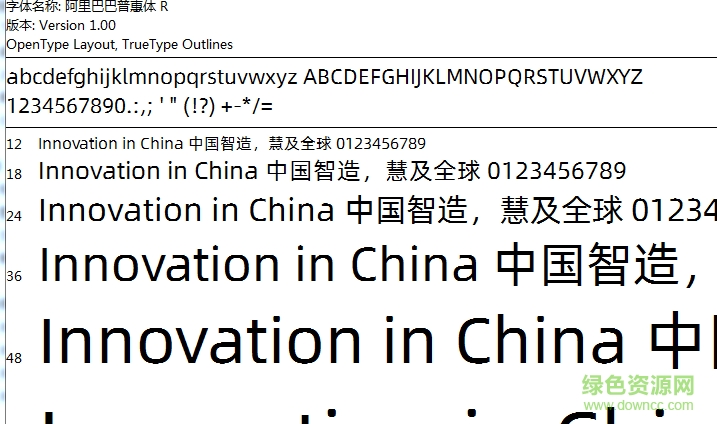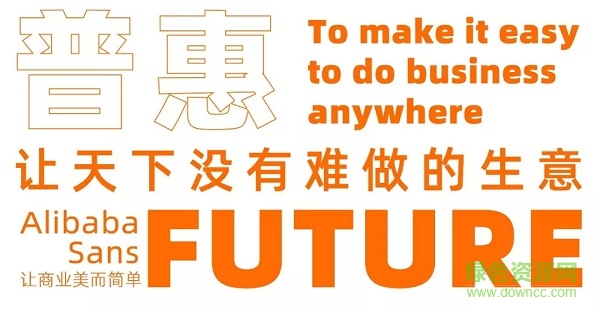
造以此字
獻(xiàn)禮阿里巴巴20周年,細(xì)入微見(jiàn)字之美,用其字品商之道,阿里巴巴普惠體,讓商業(yè)美而簡(jiǎn)單
多場(chǎng)景
中文5個(gè)字重,西文11個(gè)字重,滿(mǎn)足多業(yè)務(wù)應(yīng)用場(chǎng)景的組合表現(xiàn)需求。
全球化
收錄11.6萬(wàn)漢字,7205個(gè)拉丁字母,覆蓋173個(gè)語(yǔ)種,滿(mǎn)足阿里巴巴集團(tuán)及其生態(tài)的全球化業(yè)務(wù)需求。
年輕化
筆畫(huà)簡(jiǎn)潔,造型瘦長(zhǎng),重心較高,充分展現(xiàn)20歲阿里少年額精氣神。
這一次可免費(fèi)商用的阿里巴巴普惠體共有 Light / Regular / Medium / Bold / Heavy 5個(gè)字重,其中 L/R/M/B 4個(gè)字重按照 GB18030 字符集標(biāo)準(zhǔn)制作,各包含 28983 個(gè)字符,而 H 則遵循 GB2312 標(biāo)準(zhǔn),包含 8213 個(gè)字符,西文部分漢儀字庫(kù)西文組擴(kuò)展了日文假名、漢語(yǔ)拼音、臺(tái)灣注音符號(hào)等,最終共計(jì) 124145 個(gè)字符??梢詽M(mǎn)足阿里巴巴集團(tuán)及其經(jīng)濟(jì)體公司在全球化業(yè)務(wù)下的多個(gè)應(yīng)用場(chǎng)景需求。
據(jù)阿里巴巴定制字體項(xiàng)目負(fù)責(zé)人、阿里巴巴集團(tuán)品牌-高級(jí)創(chuàng)意設(shè)計(jì)專(zhuān)家羿光介紹,從去年 6 月至今,整套阿里巴巴普惠體的設(shè)計(jì)歷時(shí) 10 個(gè)月,“不僅要包含突顯企業(yè)品牌個(gè)性的標(biāo)題字,還要囊括更為實(shí)用的內(nèi)文字,兼顧多個(gè)場(chǎng)景下的應(yīng)用……這么大體量的字體設(shè)計(jì)并面向全場(chǎng)景開(kāi)放授權(quán)免費(fèi)商用,開(kāi)創(chuàng)了中國(guó)企業(yè)造字的先河?!?/p>
中文字體多采用現(xiàn)代簡(jiǎn)潔的筆畫(huà),造型上偏瘦長(zhǎng),并將字的重心提高,以展現(xiàn) 20 歲阿里巴巴少年的精氣神。字體筆畫(huà)上也做了一些簡(jiǎn)化,如標(biāo)題字省略出腳部分,更顯簡(jiǎn)潔。
不同于以往的家族字統(tǒng)一化處理,阿里巴巴普惠體針對(duì)不同字重的使用場(chǎng)景,對(duì)細(xì)節(jié)做了區(qū)別化處理。其中 L/R/M 較細(xì)的字體更適用于長(zhǎng)文閱讀,貼近底部的“口”字保留了出腳,更好的平衡了閱讀時(shí)的流暢感,而 B/H 兩款較粗的字體更適用于標(biāo)題場(chǎng)景,為了保證簡(jiǎn)潔的質(zhì)感,切除了出腳,從而更容易體現(xiàn)出塊面感。
家族字體的不同粗細(xì)我們稱(chēng)之為”字重“,不同字重的字體承擔(dān)著不同的作用,同時(shí)也有不同的使用規(guī)則。越細(xì)的字體反而不適用于字號(hào)非常小的字,具體的使用效果要在實(shí)際應(yīng)用中去測(cè)試,從而選擇出字重合適的字體。
去年阿里巴巴與漢儀合作,發(fā)布了 6 款智能字體。通過(guò)技術(shù)手段,為商家生成了超過(guò) 1700 萬(wàn)條視頻。只有真正做到為每個(gè)人服務(wù),才能回歸商業(yè)與設(shè)計(jì)的根本。
阿里巴巴設(shè)計(jì)的阿里巴巴普惠體」,希望能夠讓阿里巴巴的普惠精神,讓整個(gè)生態(tài)的設(shè)計(jì)師、合作伙伴因?yàn)槲覀兤脚_(tái)的賦能,真正得到實(shí)惠。
這是一款由中國(guó)企業(yè)首次發(fā)布的可面向全場(chǎng)景使用的免費(fèi)商用正文字體。以「普惠」之名誕生,這也意味著這款字體肩負(fù)著比一般企業(yè)品牌字更重要的使命──它還將開(kāi)放商業(yè)授權(quán)給所有個(gè)人和商家,讓更多用戶(hù)可以免費(fèi)使用這款阿里巴巴字體,以普惠設(shè)計(jì)賦能商家生態(tài),實(shí)現(xiàn)阿里巴巴設(shè)計(jì)「讓商業(yè)美而簡(jiǎn)單」的愿景。
青云表示,「20 歲的阿里正全速奔跑在全球化的軌道上,我們迫切需要一款統(tǒng)一的官方字體來(lái)構(gòu)建阿里巴巴品牌的一致性和完整性,從而讓大家更好地認(rèn)識(shí)阿里巴巴,更懂我們的業(yè)務(wù)?!?/p>
這一次可免費(fèi)商用的阿里巴巴普惠體共收錄 116,895 個(gè)全形漢字(含 5 個(gè)字重),西文 Alibaba Sans 共 7,205 個(gè)拉丁字母(2 種風(fēng)格、共 11 個(gè)字重),覆蓋 172 個(gè)語(yǔ)種(覆蓋大部分歐語(yǔ)國(guó)家),并可以滿(mǎn)足阿里巴巴集團(tuán)及其經(jīng)濟(jì)體公司在全球化業(yè)務(wù)下的多個(gè)應(yīng)用場(chǎng)景需求。